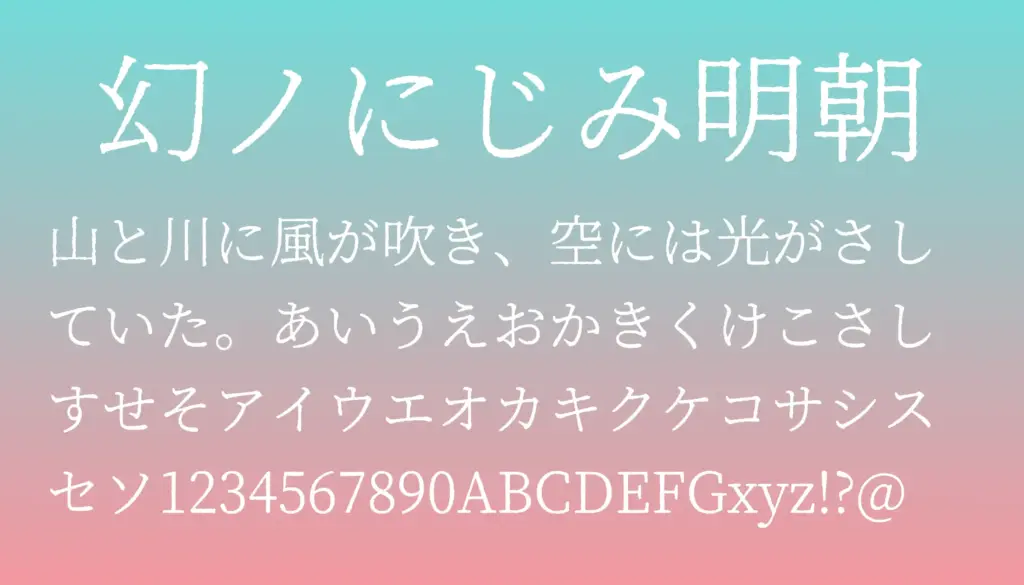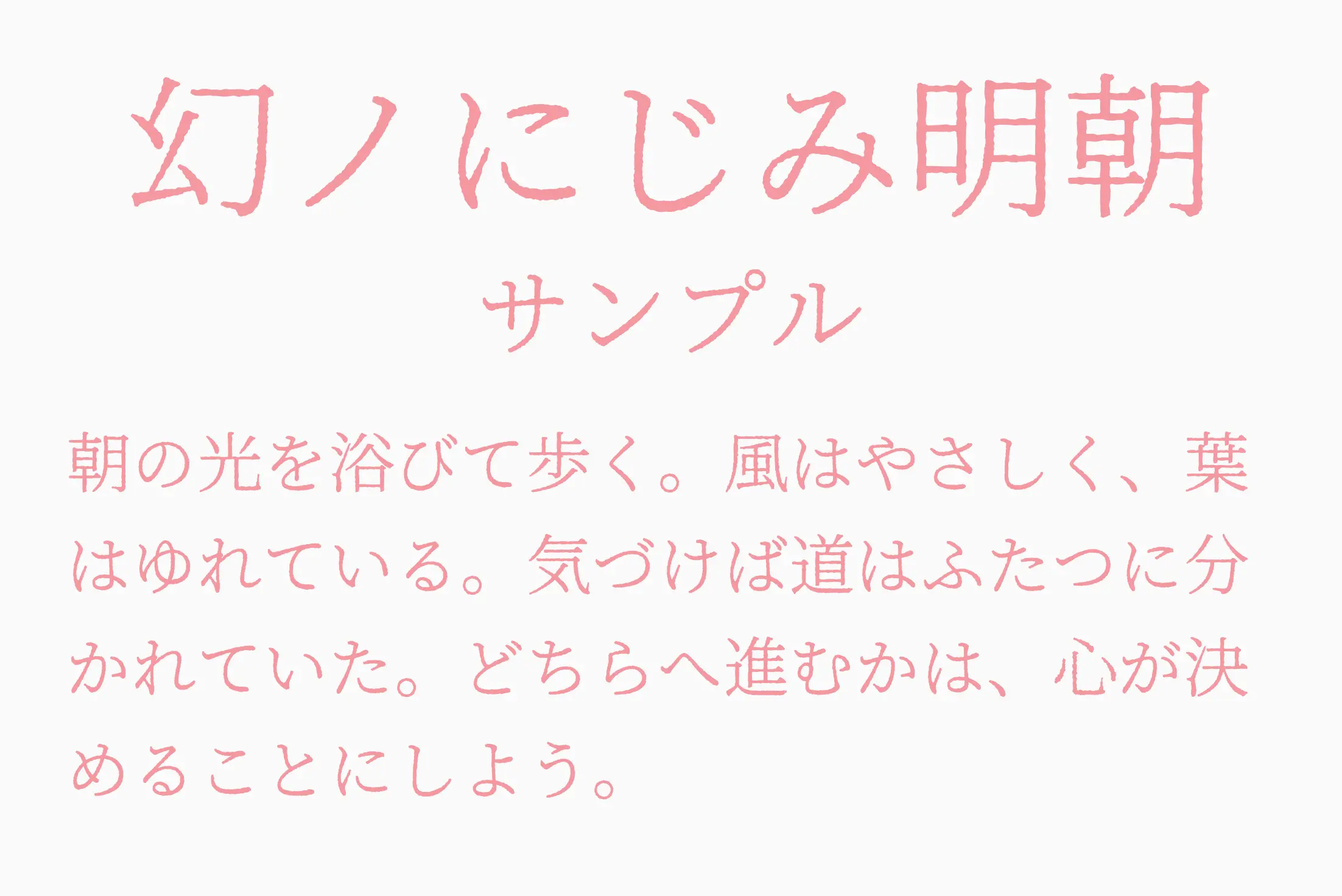
Source Han Serif をベースに、インクにじみやガタガタ線をあえて活かしたデジタルレトロな明朝体フォントです。縦横の強弱とセリフのある明朝体の骨格を残しつつ、ざらついた紙や活版印刷のにじみをイメージ。年賀状・ポスター・DTPなど、手作り感と温かみを持たせたいデザインに最適です。
幻ノにじみ明朝